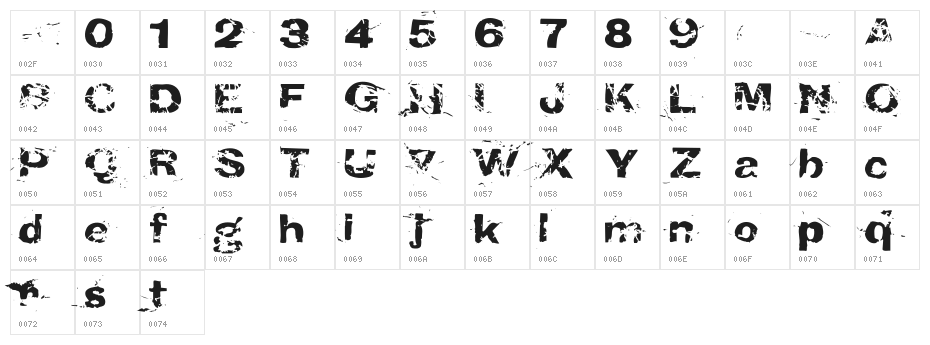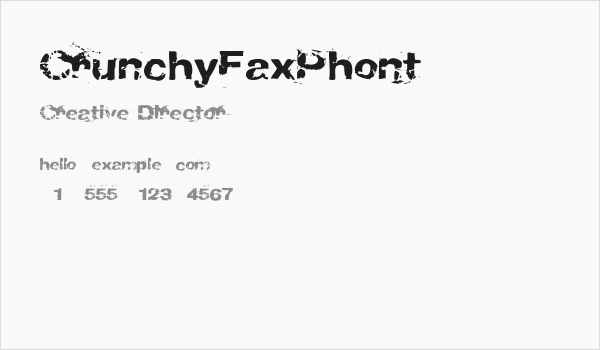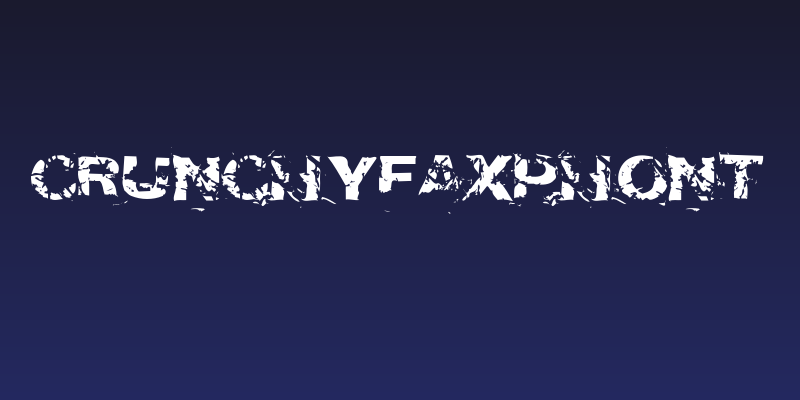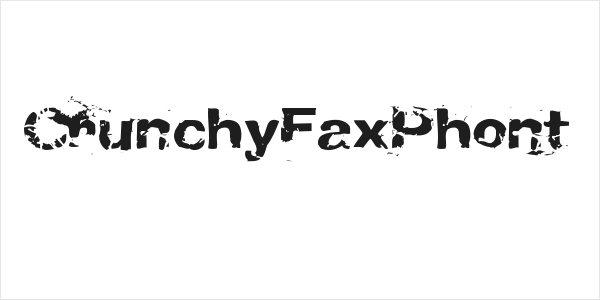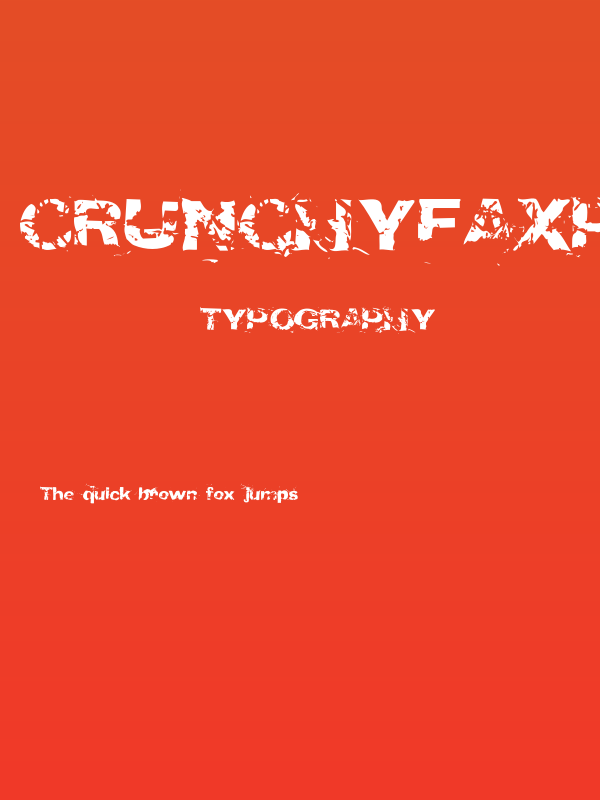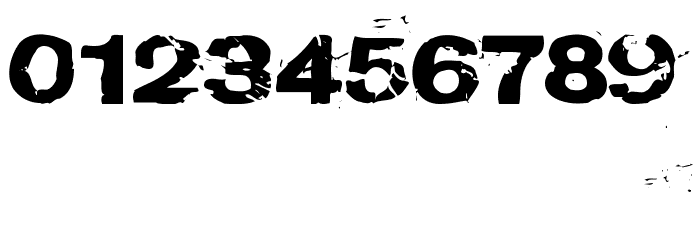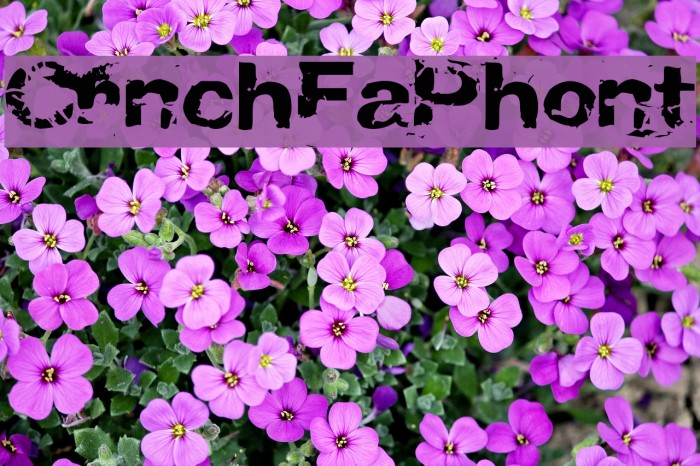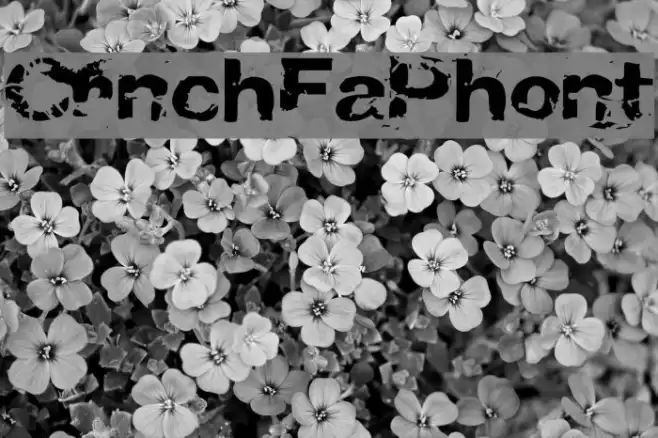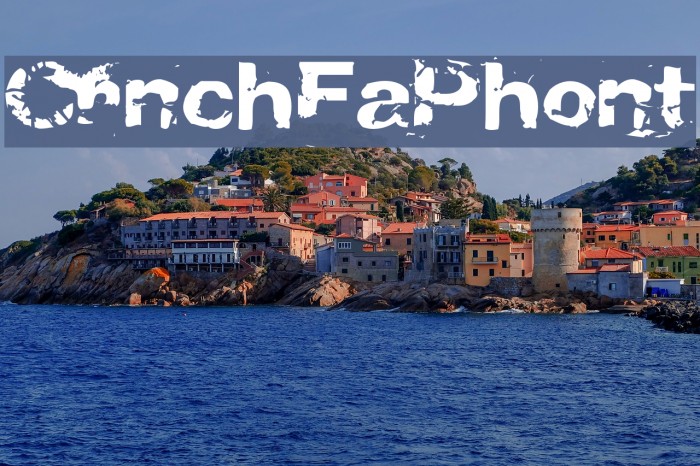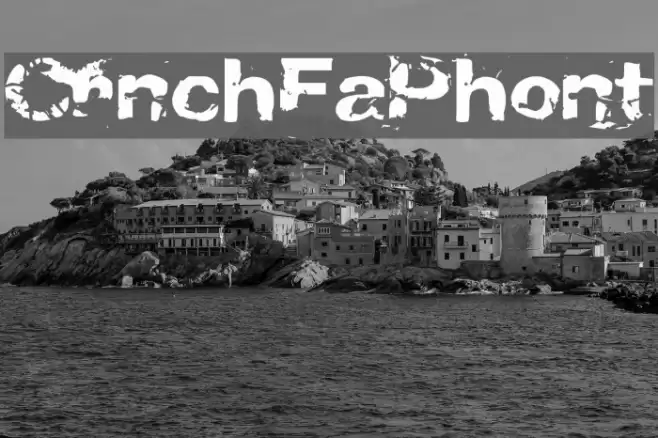
CrunchyFaxPhont Font
| 全体的なスタイル | Grunge, Urban, Distressed |
| おすすめプロジェクト | Ideal for album covers, posters, streetwear branding, and any project needing a gritty, urban aesthetic. |